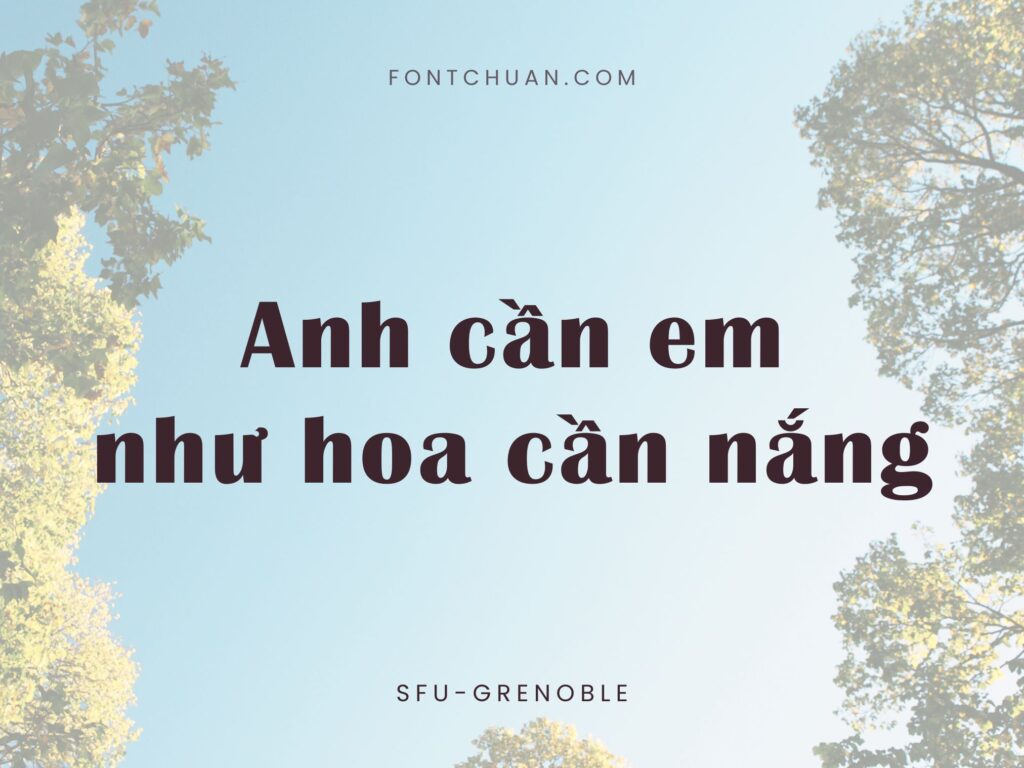
Grenoble là một kiểu chữ serif được thiết kế bởi Altsys và phát hành lần đầu vào năm 1993. Font này được sưu tầm và đăng bởi thành viên của Font Chuẩn. Grenoble nổi bật với thiết kế cổ điển, mang lại cảm giác trang nhã và dễ đọc, phù hợp cho nhiều mục đích sử dụng khác nhau.
Về mặt thiết kế, Grenoble có các đường nét tinh tế, tỷ lệ cân đối và độ tương phản giữa các nét dày và mỏng, tạo cảm giác thanh lịch và chuyên nghiệp. Font này phù hợp cho các ứng dụng như thiết kế sách, tạp chí, in ấn cao cấp và các ấn phẩm cần sự trang trọng. Các ngành nghề như giáo dục, xuất bản, nghệ thuật và quảng cáo có thể tận dụng kiểu chữ này để tạo dấu ấn đặc biệt trong truyền thông.